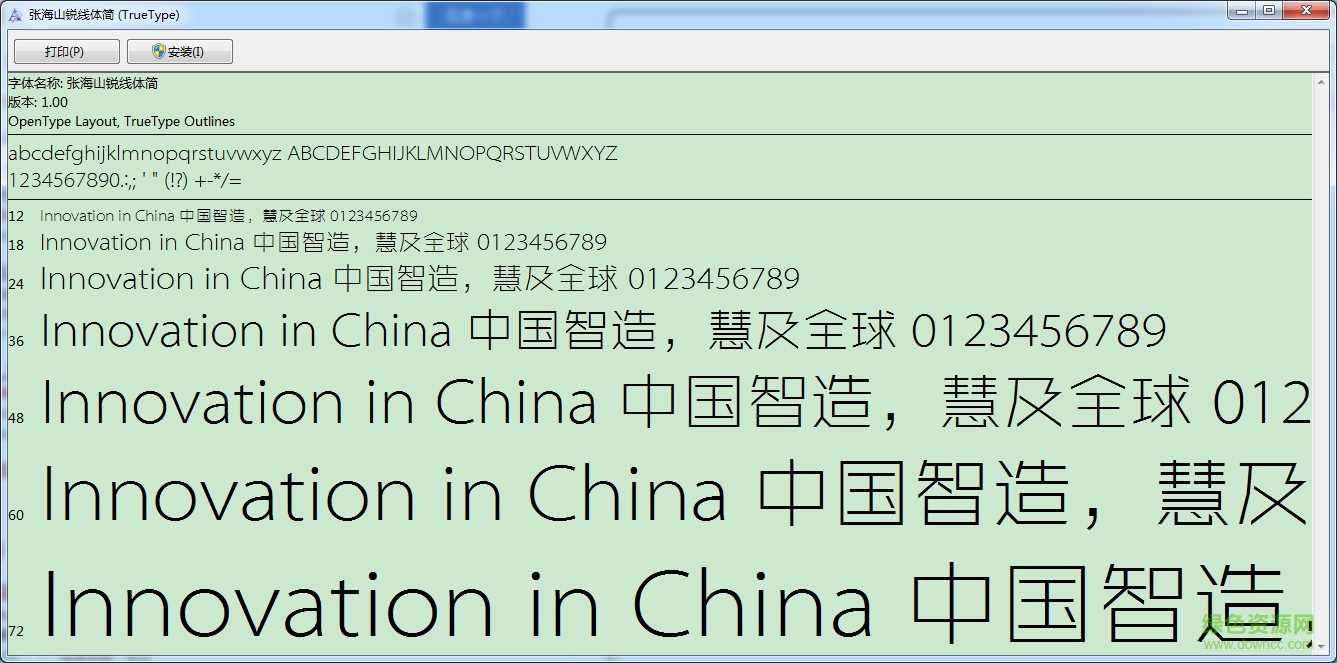
zhsrxt gbk1 0是什么字體?zhsrxt gbk1 0即為張海山銳線體簡(jiǎn)字體,字體大方得體,支持漢字、中文、英文等多種方式輸入顯示,一鍵安裝便可使用,極具美感時(shí)刻彰顯個(gè)人魅力??靵砭G色資源網(wǎng)下載體驗(yàn)吧!
本字體是一款優(yōu)秀的藝術(shù)漢字字體,張海山銳線體簡(jiǎn)是根據(jù)書法家張海山的書法作品制作的字體,本字體具有筆畫清晰纖細(xì)的優(yōu)點(diǎn),多用于廣告設(shè)計(jì)等用途。